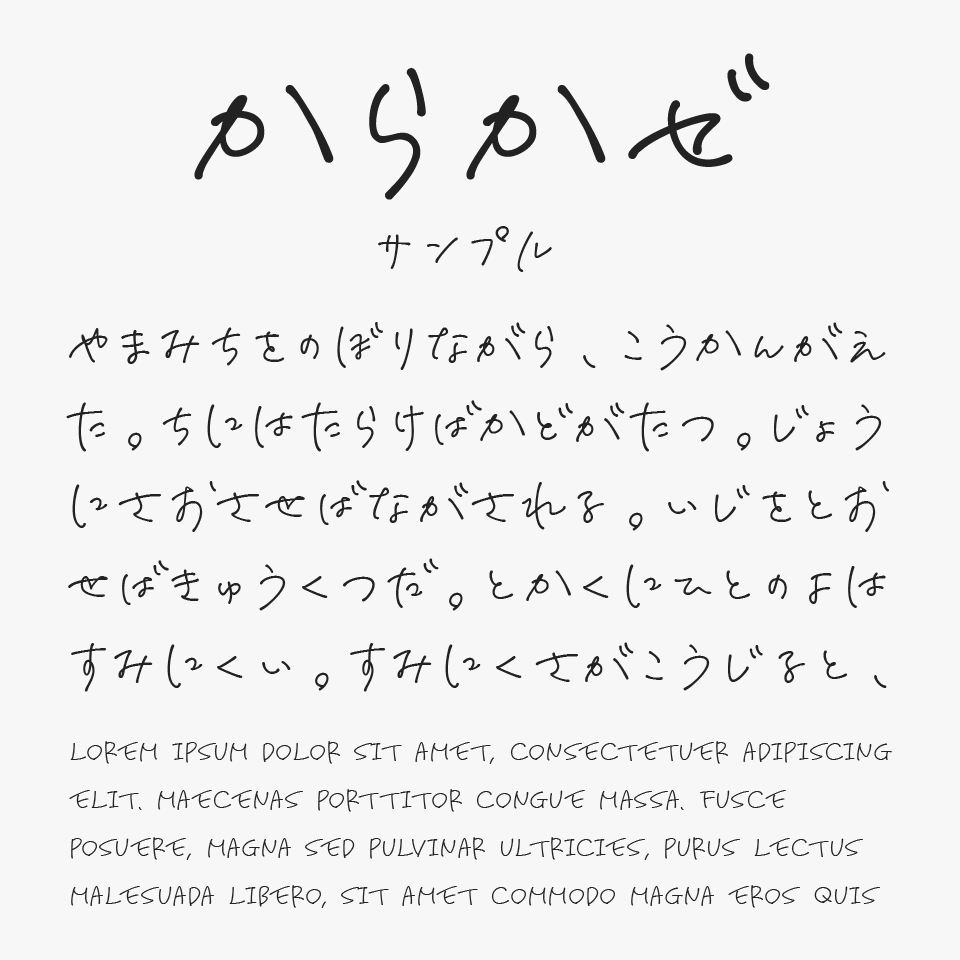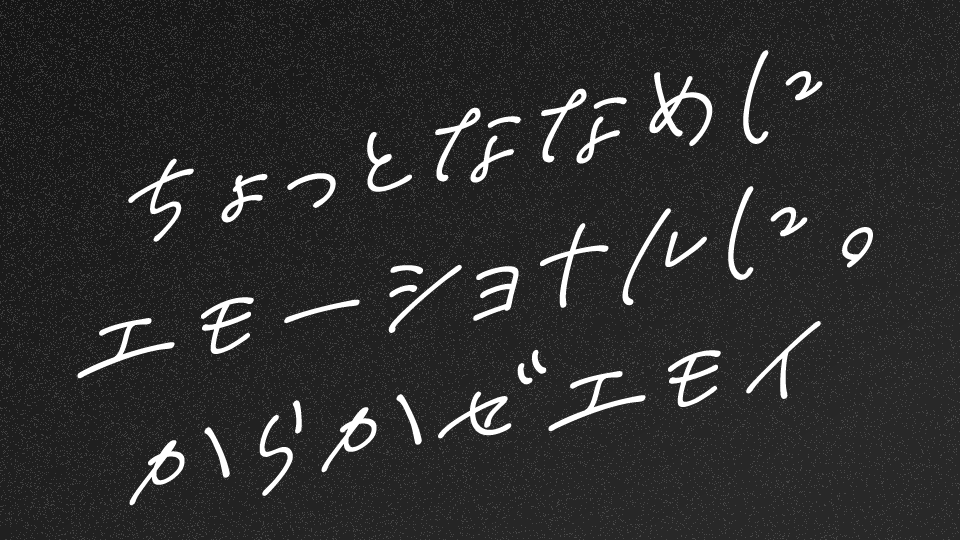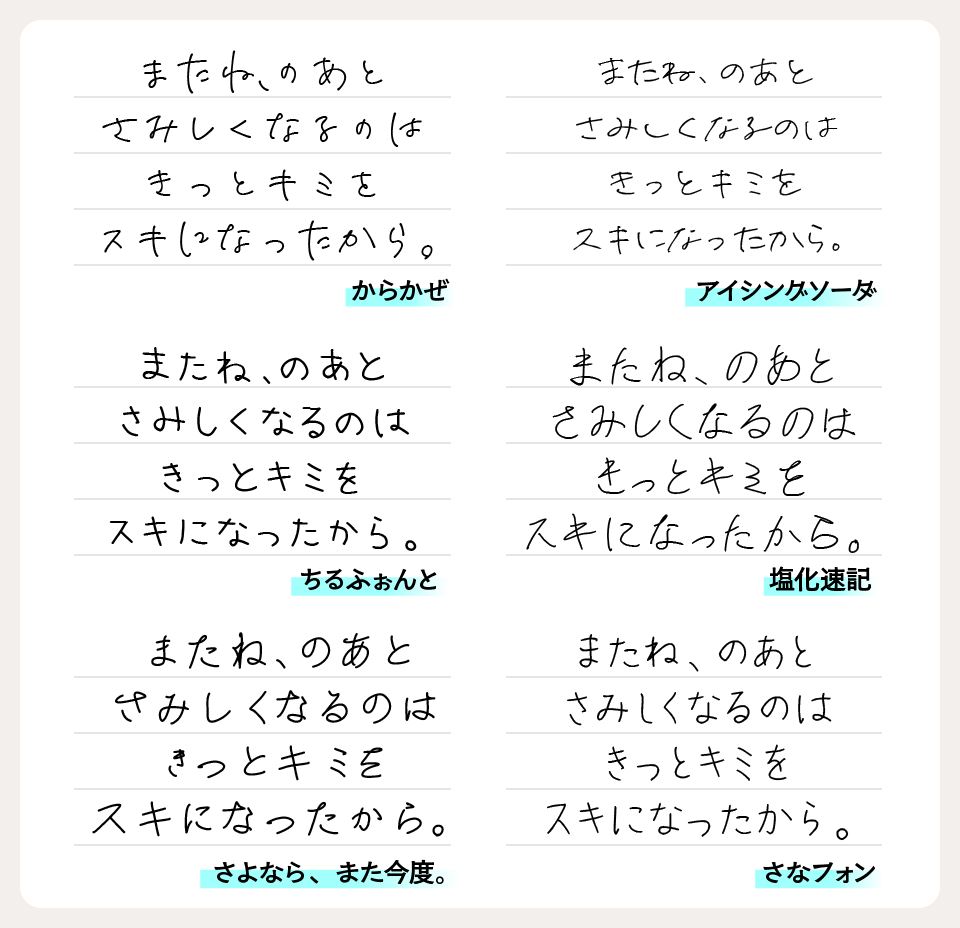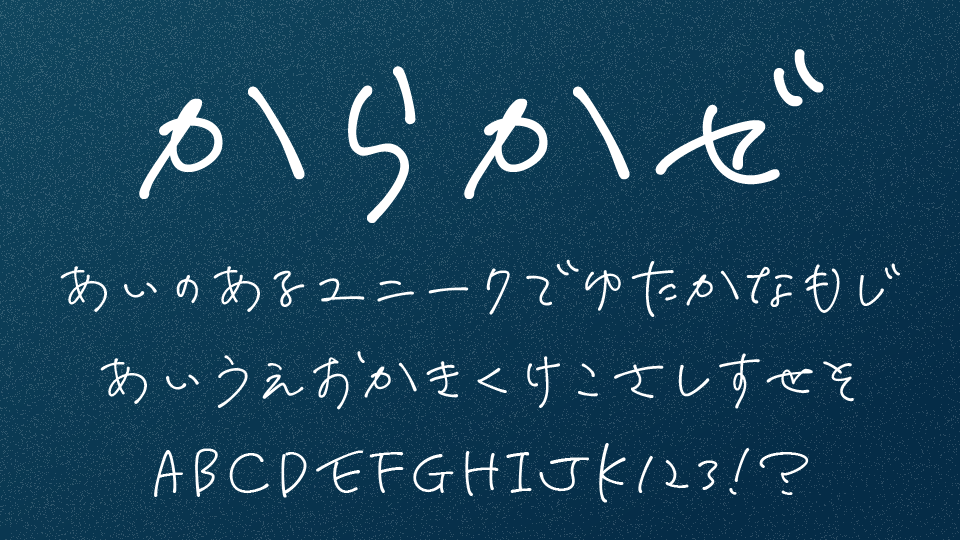
からかぜフォントは、作者様いわく『冬の空気のような』からっと乾いたニュアンスを持つ、走り書き風の手書きフォントです。
さらっと流れるような線の動きには、ラフさの中にどこか洗練された雰囲気があり、手書きフォントらしい自然さと、大人っぽい空気感が絶妙に混ざり合っています。
力を入れすぎていない軽やかな筆跡によって、気取らない“今どき感”や、少し切なさを感じるようなエモーショナルな雰囲気も魅力です。
カジュアルすぎず、おしゃれにまとまるバランス感があるため、MV風デザインやファッション系ビジュアル、雑誌風タイトル、SNS投稿画像などとも相性抜群です。
走り書きや殴り書きのような勢いがある文字になっているので、短いタイトルやコピー、歌詞、詩歌などあまり長くない文章を軽やかに使うのに非常にマッチしています。
作者様の手書きのクセがあえて残っているフォントなので、人肌感が感じる文字なので、キャラクターの書き文字やサイン文字としても違和感なく使えます。
このように短い一言メッセージのような使い方をするとめちゃエモい。
からかぜを、ほかのエモーショナルな雰囲気を持つ手書きフォントと比較してみると、さらっと走り書きをしたような“乾いた空気感”や力の抜けた自然さが魅力のフォントです。
フォントと比較してみると、ラフさをそのまま活かした“脱力感”が特に魅力的なフォントです。
比較フォントは、「アイシングソーダ」「ちるふぉんと」「塩化速記」「さよなら、また今度。」「さなフォン」と使用していますが、どのフォントも独特な書き味がエモい雰囲気をもつ手書きフォントなので、ぜひあわせてチェックしてみてください。
収録文字は、ひらがな・カタカナ・漢数が一〜十の数字のみとなっているので、漢字が入ってるような文字列の場合は、漢字は別のフォントに置き換えて混植フォントと使うのも良いかもしれません。
| 漢字の収録数 | △(漢数字(一〜十)のみ) |